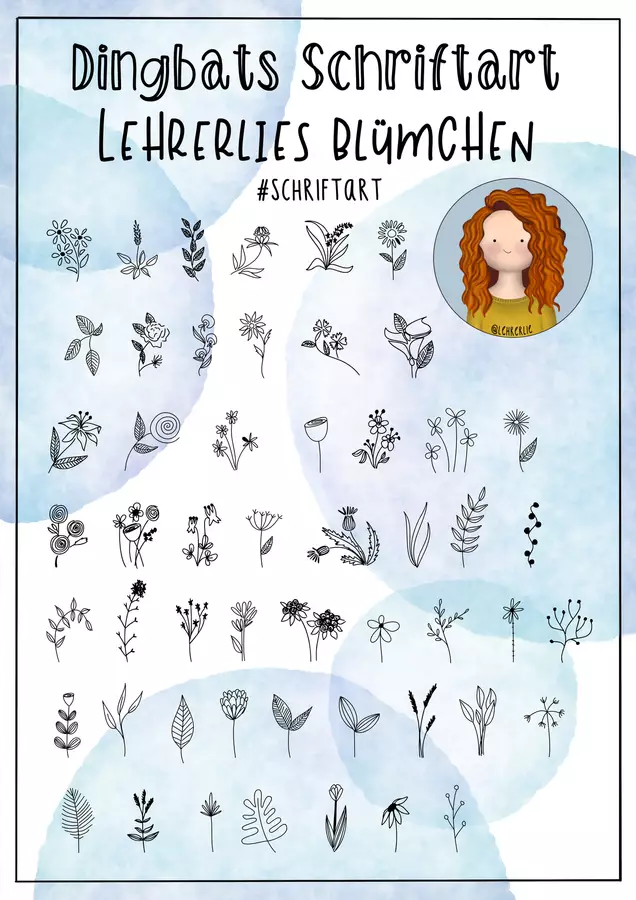
selbst erstellte Cliparts/Grafiken - Dingbats-Schriftart: Lehrerlies Blümchen // Sketchnotes - Pinselkomponistin - Deckblatt
In diesem Material erhaltet ihr eine Dingbats-Schriftart. Sie besteht aus über 25 Blumen im Sketchnote-Style, mit welchen ihr eure Materialien in allen gängigen Programmen super einfach gestalten könnt. Einfach die Schriftart installieren und mit dem beiliegenden Fontposter das gewünschte Element auswählen.
Dingbats-Schriftart: Lehrerlies Blümchen // Sketchnotes